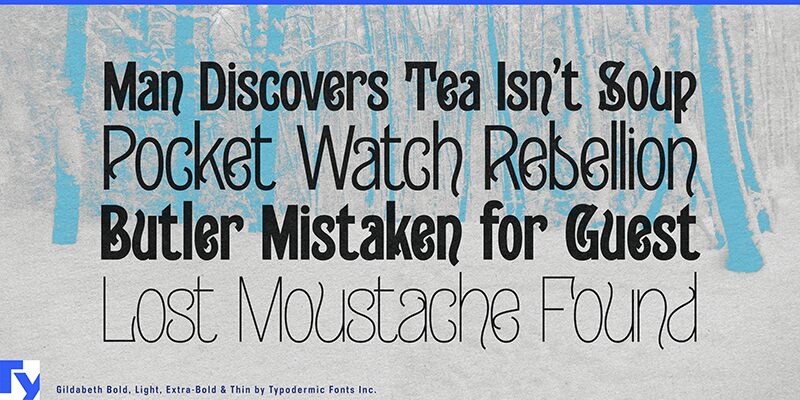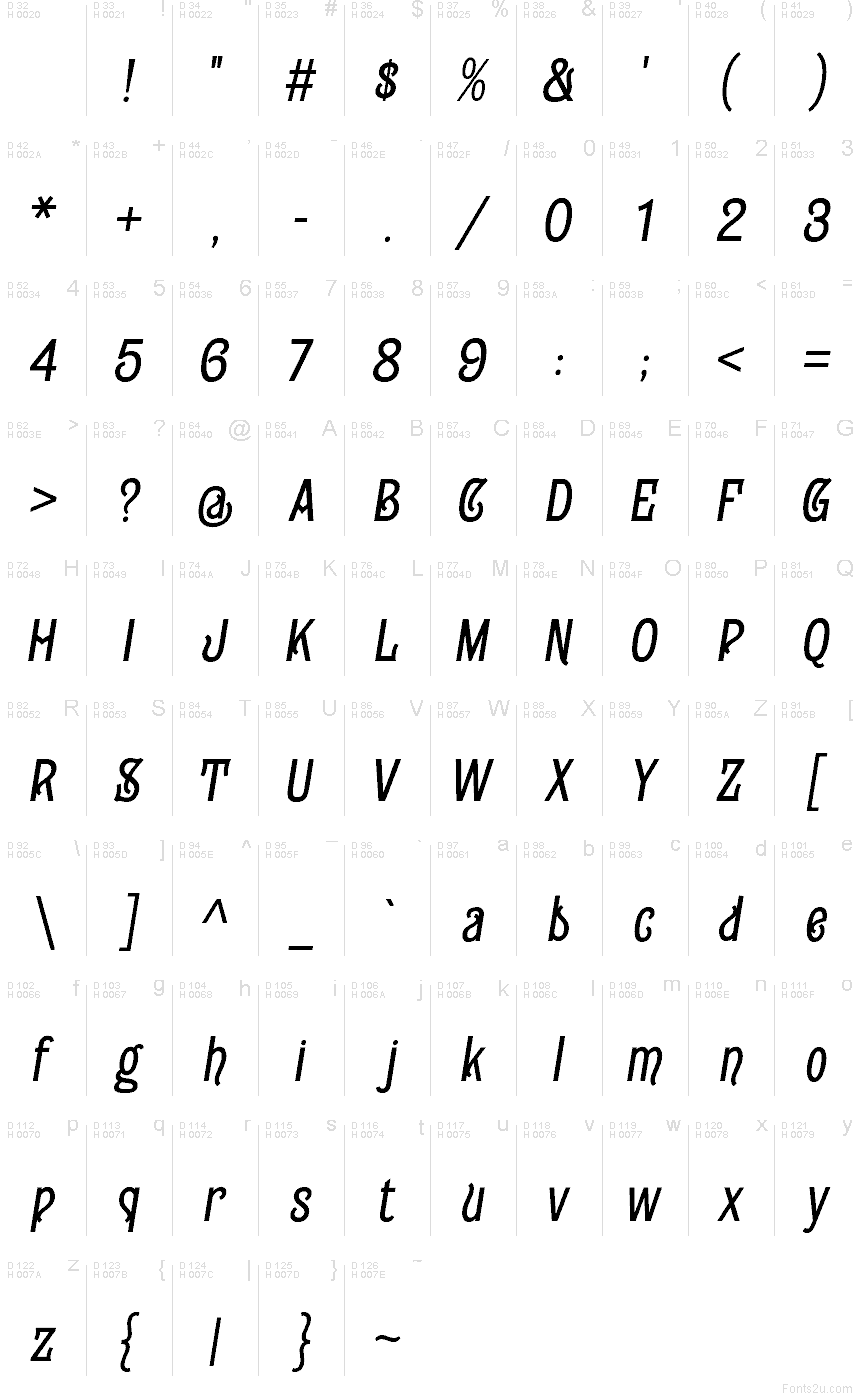
Gildabeth est une police sans empattement étroite et très contrastée, inspirée par les lettrages d'affichage excentriques de la fin du XIXe siècle. S'inspirant de modèles tels que Campanile et Attic, elle conserve leur modulation singulière et leurs courbes théâtrales tout en épurant le superflu pour un usage contemporain.
Ses proportions élancées apportent beaucoup de caractère, même dans les espaces restreints, ce qui la rend idéale pour les titres, les affiches, les couvertures de livres et une image de marque audacieuse. Des traits marqués confèrent au design un caractère affirmé et artisanal, insufflant une touche vintage et une énergie expressive à la typographie moderne.